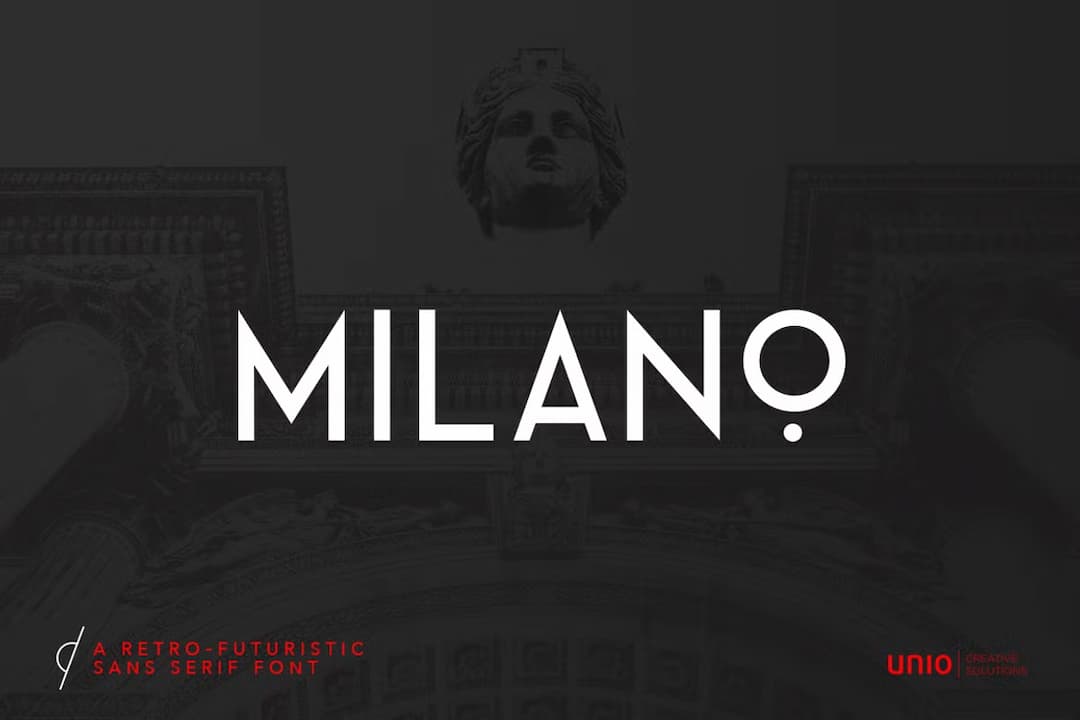
さ! 冬季五輪もあったということで(終わったわ)こちら。レトロなイタリアンアールデコのサンセリフディスプレイ。ジオメトリックなアール・デコ風味の書体で、シャープな雰囲気ながら低めのセンターバーがちょっとした可愛らしさを醸し出している。アール・デコなのでレトロではありつつ、モダンさもあって現在でも大変使いやすい書体だろう。大文字のみでスモールキャップス。オマケで、9種類の赤いトーンを付与する Lightroom プリセットが付属している。